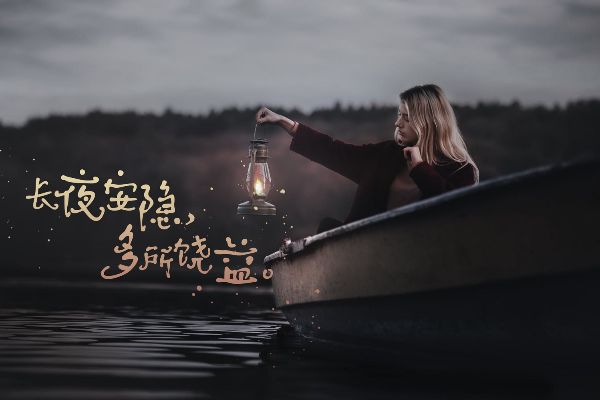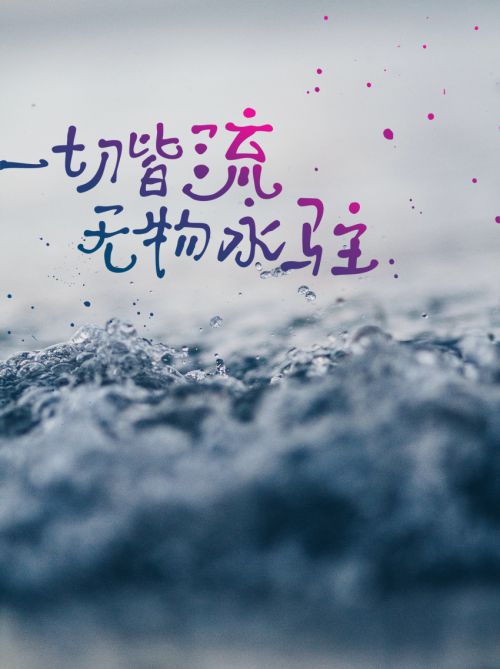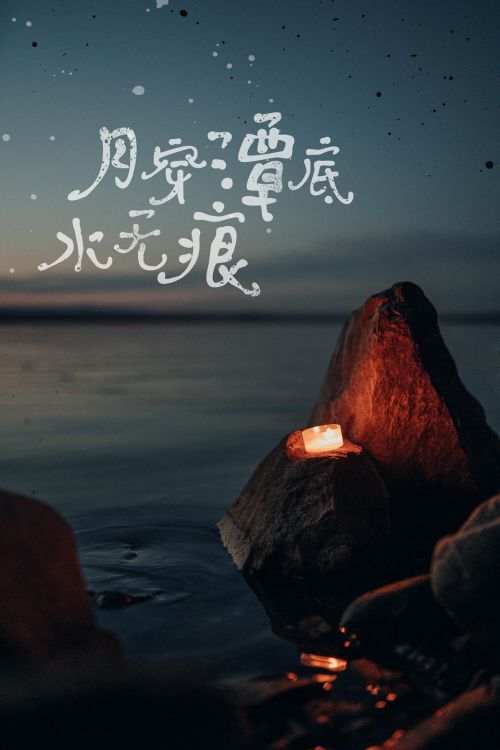
默陌菩提禅书
默陌菩提禅书是一款水墨手写体,字形拙朴,笔画圆润,形态如枝藤盘错,颇有禅风古意。
默陌
默陌是一名独立设计师,从事字体创意设计多年,目前已发布默陌水墨手迹系列、默陌硬笔手写体系列、默陌奇趣可爱手写系列等30余款字体字库作品,广泛应用于平媒、影视、手机端显示等场景。默陌字体字形多变,风格多元,坚持致力于传统书法意趣和现代手写个性的有机融合,创作出更多美好的原创手迹。